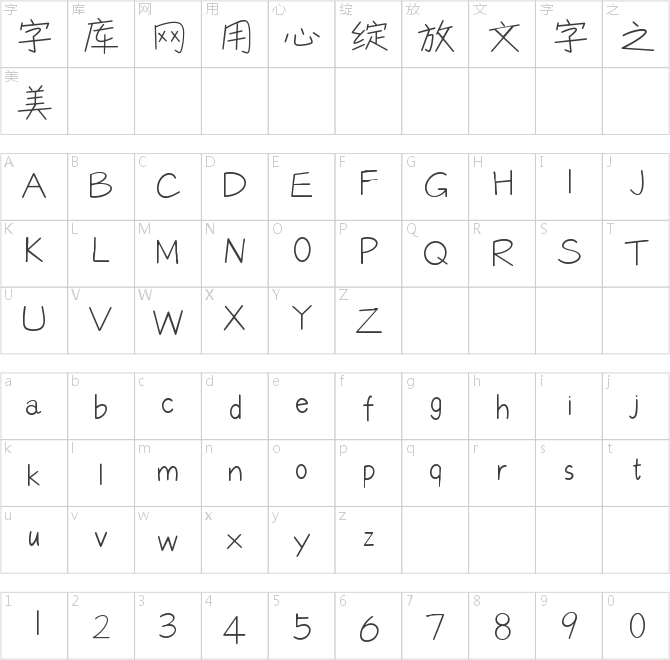
字魂212號(hào)-浪漫情書體是一款硬筆手寫字,字體的起筆、收筆和折筆處呈圓形,筆畫圓轉(zhuǎn)流暢,字體結(jié)構(gòu)活潑有趣。適用于品牌廣告和產(chǎn)品包裝設(shè)計(jì),以及社交網(wǎng)絡(luò)個(gè)性化用字。
字魂212號(hào)-浪漫情書體字體zihun212hao-langmanqingshuti字庫是一款讓人賞心悅目、百看不厭的中文字體,適合各類廣告和產(chǎn)品包裝設(shè)計(jì)應(yīng)用,字體大小7.77MB,格式為ttf字體,上傳用戶是喜歡戳爺,作者/版權(quán)方為字魂